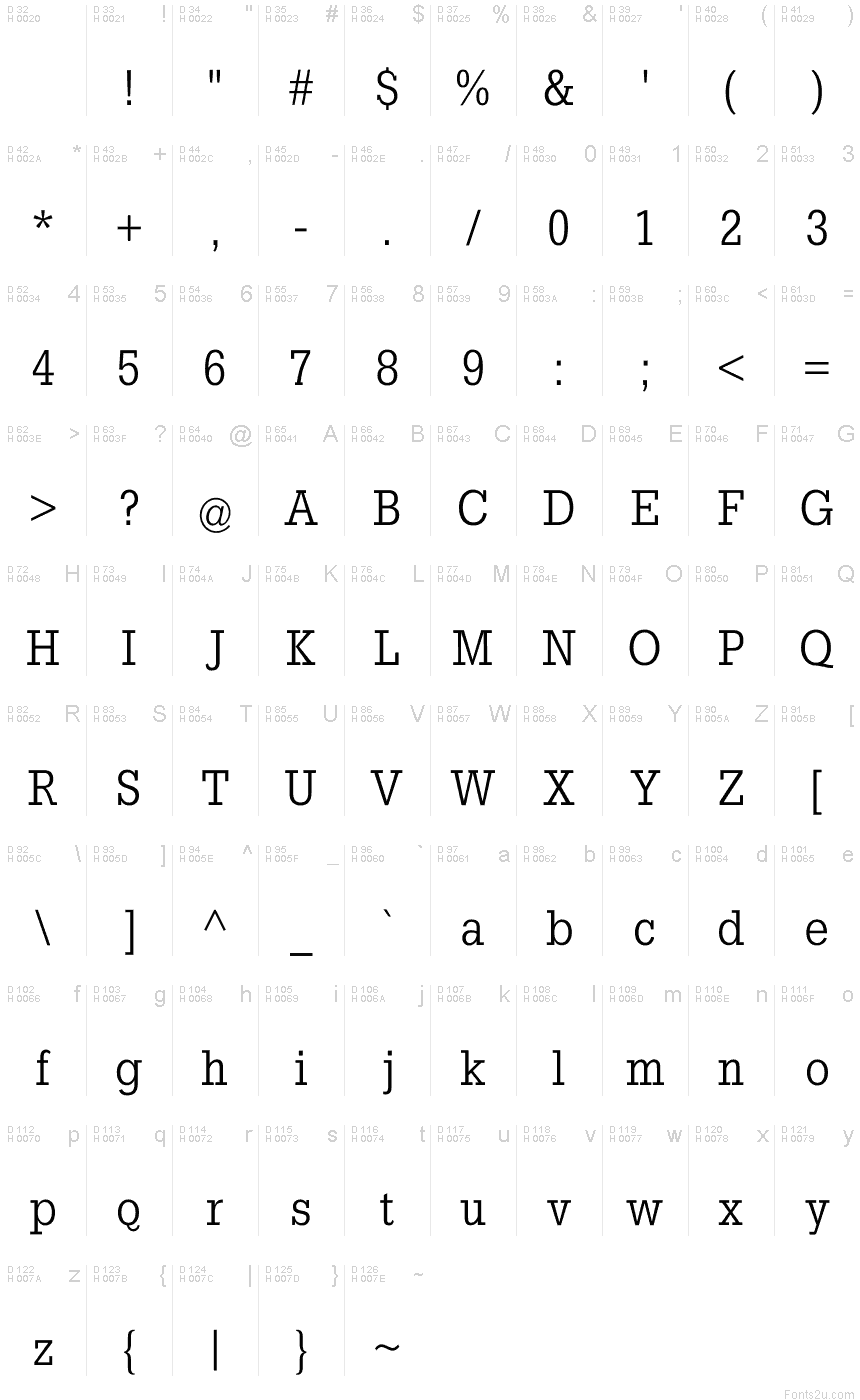
SlabTallX
Slab Tall X od M. Klein to darmowy, wysoki krój typu slab serif o smukłej, plakatowej charakterystyce. Litery wznoszą się dzięki wąskim proporcjom i solidnym, kwadratowym szeryfom, łącząc w sobie klasyczny rytm z surową, pionową estetyką dawnych reklam.
Krój ten pasuje do nagłówków redakcyjnych, okładek książek, opakowań, plakatów oraz brandingu, który potrzebuje kompaktowego pisma nagłówkowego z nutą minionych lat. Jako darmowy font świetnie sprawdzi się również w tytułach, cytatach czy inicjałach, ponieważ pionowe wydłużenie i wyraziste, tępe zakończenia szeryfów nadają krótkim wyrazom czysty, stanowczy wygląd.